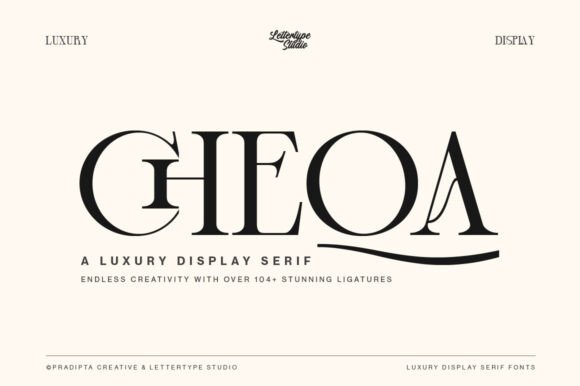
Cheqa
Cheqa – A Timeless Typeface for Luxury Branding
Se você procura uma fonte que una sofisticação, elegância e versatilidade, Cheqa é a escolha certa. Inspirada na tipografia do século XVIII, essa fonte serifada traz um toque clássico que se destaca em qualquer projeto, seja ele editorial, web ou de branding.
- Design Clássico – Linhas limpas e geometria refinada transportam a elegância da era 18ª para o mundo digital.
- Versatilidade – Cheqa funciona bem em títulos, corpo de texto e logotipos, tornando-a perfeita para designers que precisam de uma solução completa.
- Luxo & Refinamento – Detalhes luxuosos e finas serifas conferem um ar de alta classe a qualquer aplicação.
- Aplicações Ideais – Branding de luxo, revistas, websites de moda, e até cartões de visita premium.
Ao escolher Cheqa, você garante que seu projeto se destaque com um visual atemporal e de alta qualidade. Experimente hoje e transforme sua marca em uma obra de arte tipográfica.